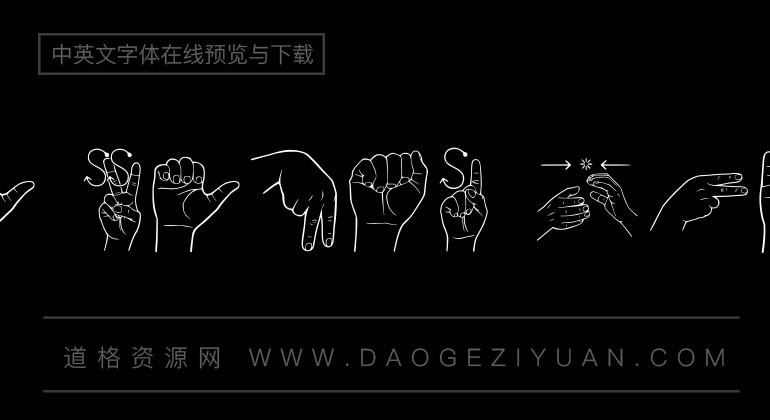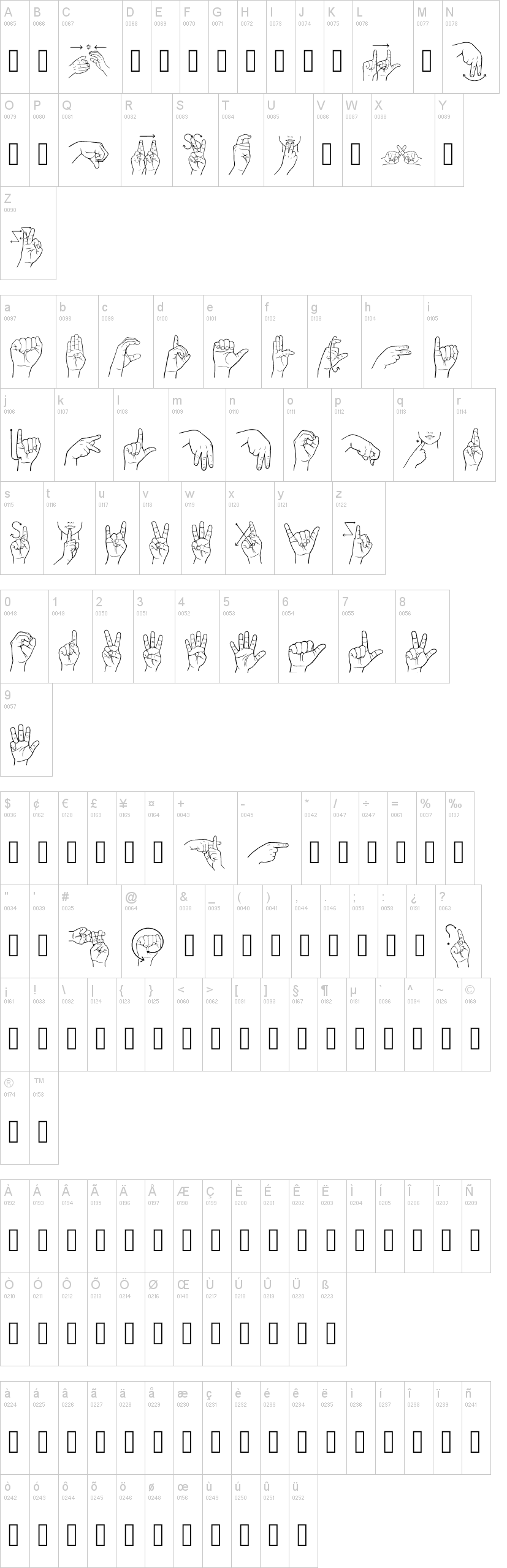
Lengua De Senas Chilena Hef
Lengua De Señas Chilena Hef 字体是一种手语字体,用于在视觉上呈现智利手语(Lengua de Señas Chilena)的手势。该字体由智利设计师 Rodrigo Ramírez Herrera 创作,旨在解决智利聋人社区面临的沟通障碍问题。 Lengua De Señas Chilena Hef 字体包括了智利手语中常用的手势符号,可以用于制作海报、卡片、传单和其他视觉设计作品,以便更好地传达信息和理解聋人社区的需求。 该字体的设计灵感来源于手语的动作和线条,它采用了简洁明了的风格,可以在不失清晰度的情况下缩小或放大,同时保持手势的清晰和可辨识性。 总之,Lengua De Señas Chilena Hef 字体是一种非常实用的字体,可以方便地呈现智利手语,有助于增进视觉传达的效果,促进聋人和听障人士与其他人之间的交流。
Lengua De Senas Chilena Hef是一款非常不错的手写艺术字体,具有很好的视觉感,适合于文化类的宣传设计、商业类品牌的广告和产品包装设计以及个性化文字排版等较多场景。